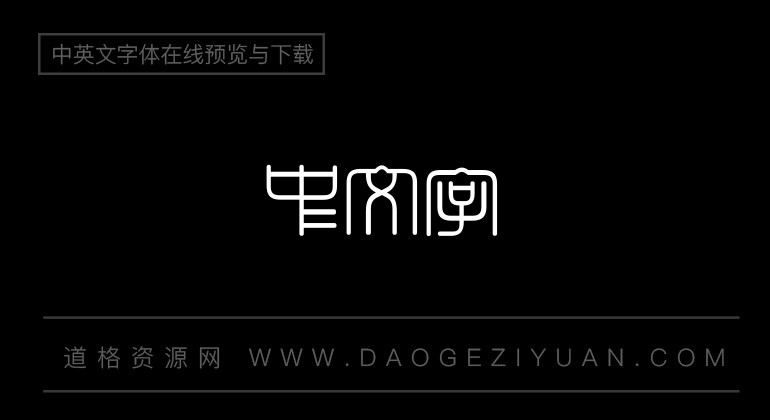
超世纪细方篆体繁
超世纪细方篆体繁是一款由超世纪字体厂推出的细方篆体字体,它的特点是笔画细腻,曲线圆润,笔画精细,结构严谨,符号清晰,可以用于书法、图形设计、文字设计等领域。
超世纪细方篆体繁是一款非常不错的手写艺术字体,具有很好的视觉感,适合于文化类的宣传设计、商业类品牌的广告和产品包装设计以及个性化文字排版等较多场景。